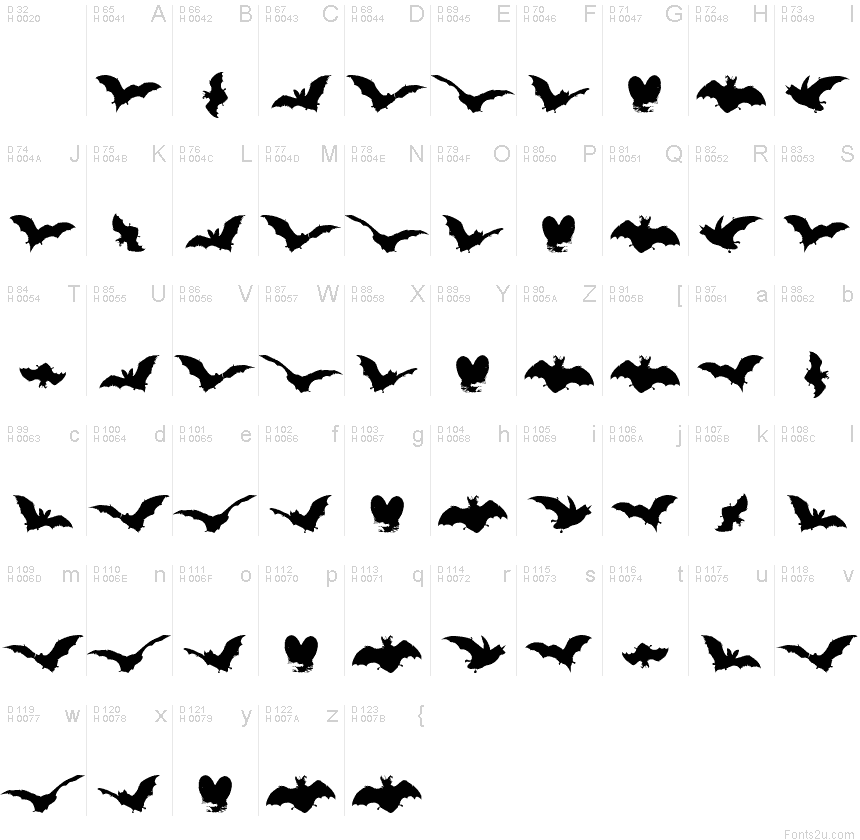
Vampyr Bats von Manfred Klein ist eine kostenlose Horror-Dingbat-Schrift, die auf Fledermaus-Silhouetten und schattigen Formen basiert. Die Zeichen wirken fast wie in der Luft schwebend und leicht zerfranst – mit spitzen Ohren, hakenförmigen Flügeln und weichen Kanten. Das Ganze wirkt weniger wie eine ordentliche Sammlung von Symbolen, sondern eher wie ein Schwarm, der über die Seite zieht.
Die Schrift eignet sich perfekt für Halloween-Poster, Flyer für Geisterhäuser, Horror-Zines, Partyeinladungen und gruselige Verpackungen, bei denen ein paar Fledermäuse sofort für Stimmung sorgen, ohne dass es weitere Illustrationen braucht. Als Gratis-Font ist er zudem ideal für Titelkarten, Kapitelanfänge und thematische Umrandungen – besonders dann, wenn man ein düsteres Flugmotiv statt schlichter Ornamente sucht.